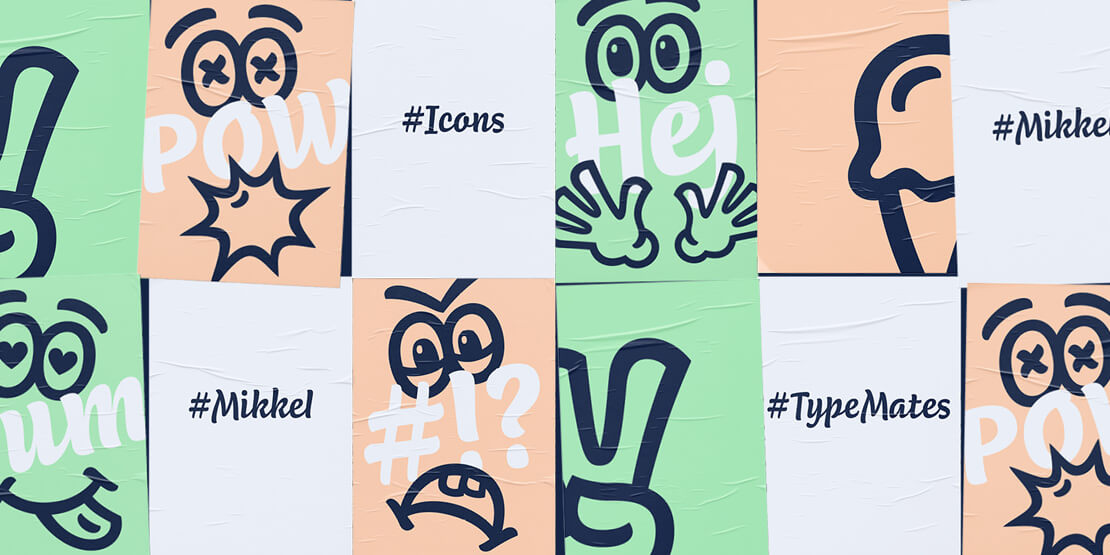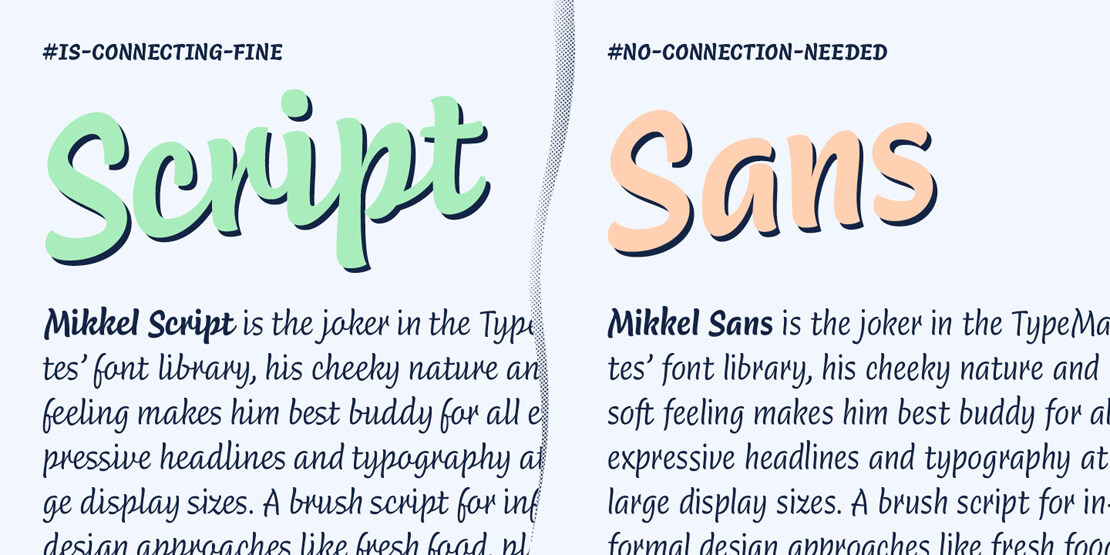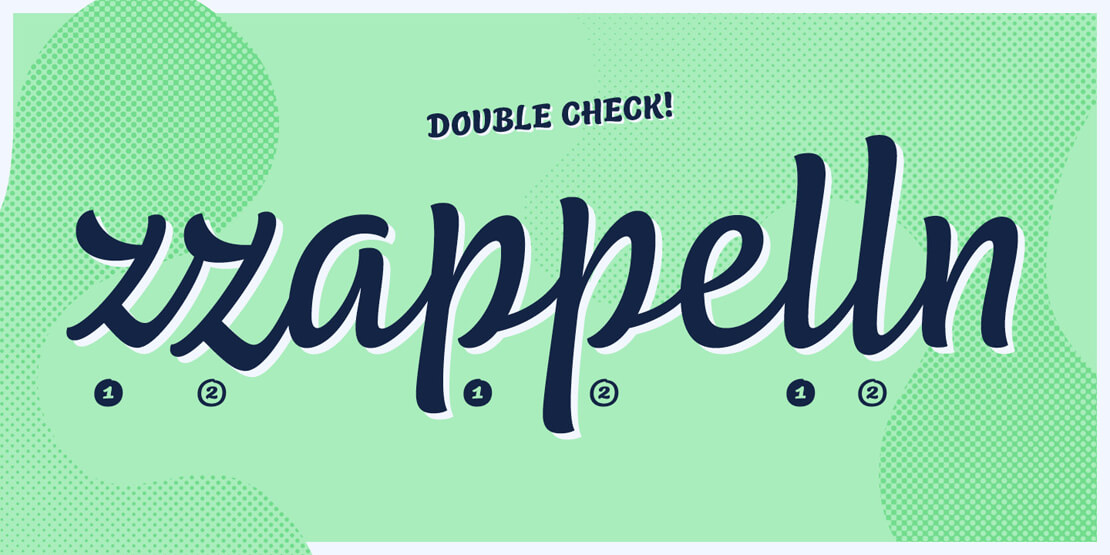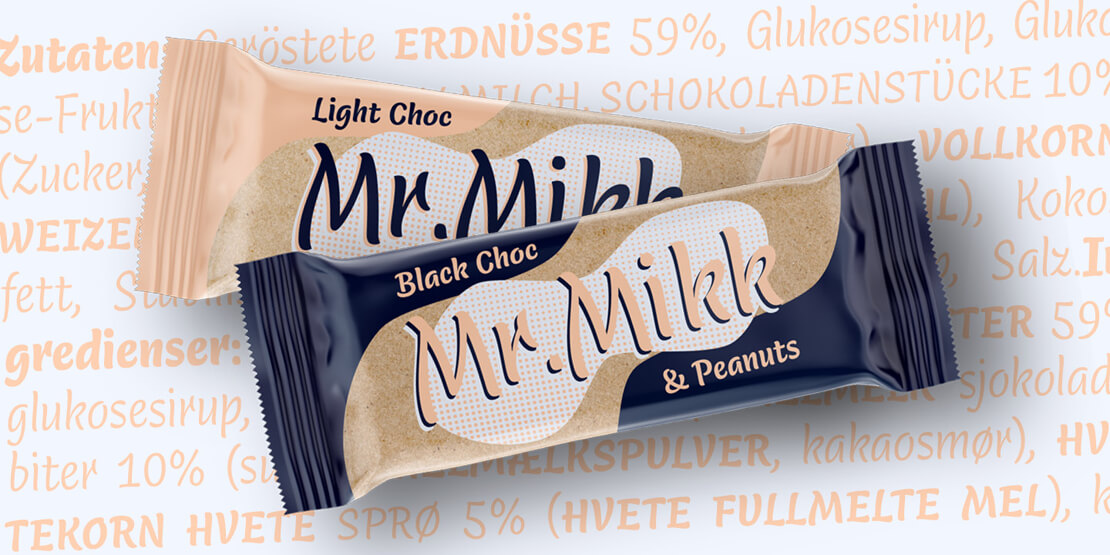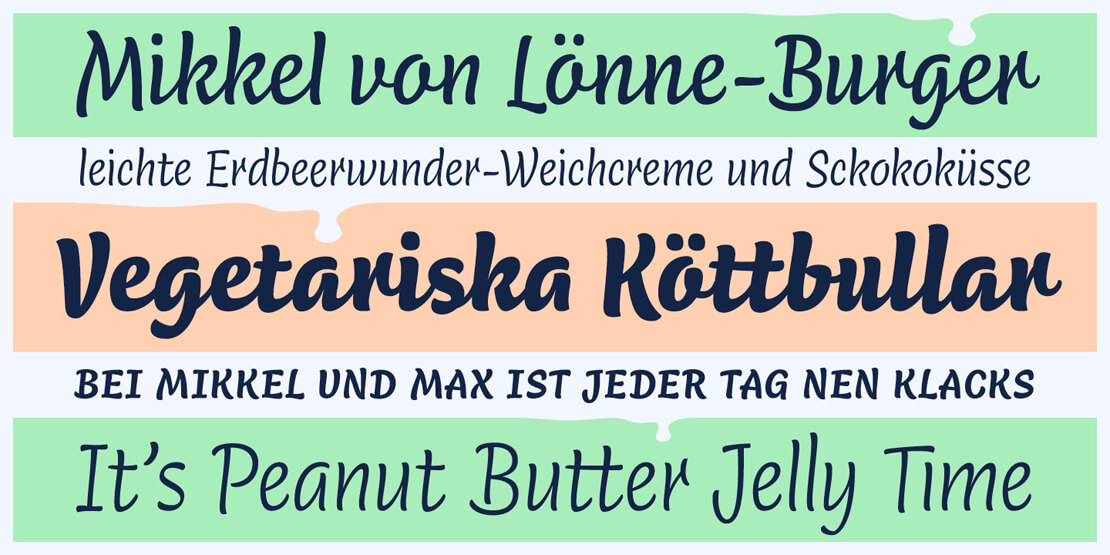
Mikkel: Sahnig-lockeres Schriftfamilien-Duo
Eine Schrift mit lässigem Charakter stellen die TypeMates vor. »Mikkel« von Nils Thomsen gibt es in einer cremigen Script-Variante sowie als »Sans«, bei der die Kleinbuchstaben nicht verbunden sind.
Die Großbuchstaben kommen schwungvoll. Die Kapitälchen wurden bewusst etwas moderater angelegt, um auch im Versalsatz eine Alternative darzustellen.
Das Ligaturen-OpenType-Feature kümmert sich um Mikkels handschriftlichen Ursprung: Doppelte Buchstaben werden automatisch durch alternative Zeichen ersetzt. So ergibt sich eine schwungvolle Schrift, die sich für Logos, Lettering und Packaging eignet. Die »Sans« kann man zudem für kurze Textabschnitte verwenden, da die Kleinbuchstaben nicht verbunden sind und hierdurch ein lesbareres Textbild entsteht.
Umfang und Features
»Mikkel Script« und »Mickel Sans« gibt es jeweils in den Schnitten Thin, Light, Regular, Bold und Black. Die Schriftfamilie hat außerdem einen »Baukasten« mit comichaften Icons im Gepäck.
Mikkel bietet rund 1.000 Glyphen pro Schnitt sowie eine weite Unterstützung der lateinischen Sprachen. OpenType-Features für den dynamischen Schriftfluss sind ebenso enthalten wie echte Kapitälchen, Textziffern, Tabellenziffern sowie hochgestellte Ziffern.